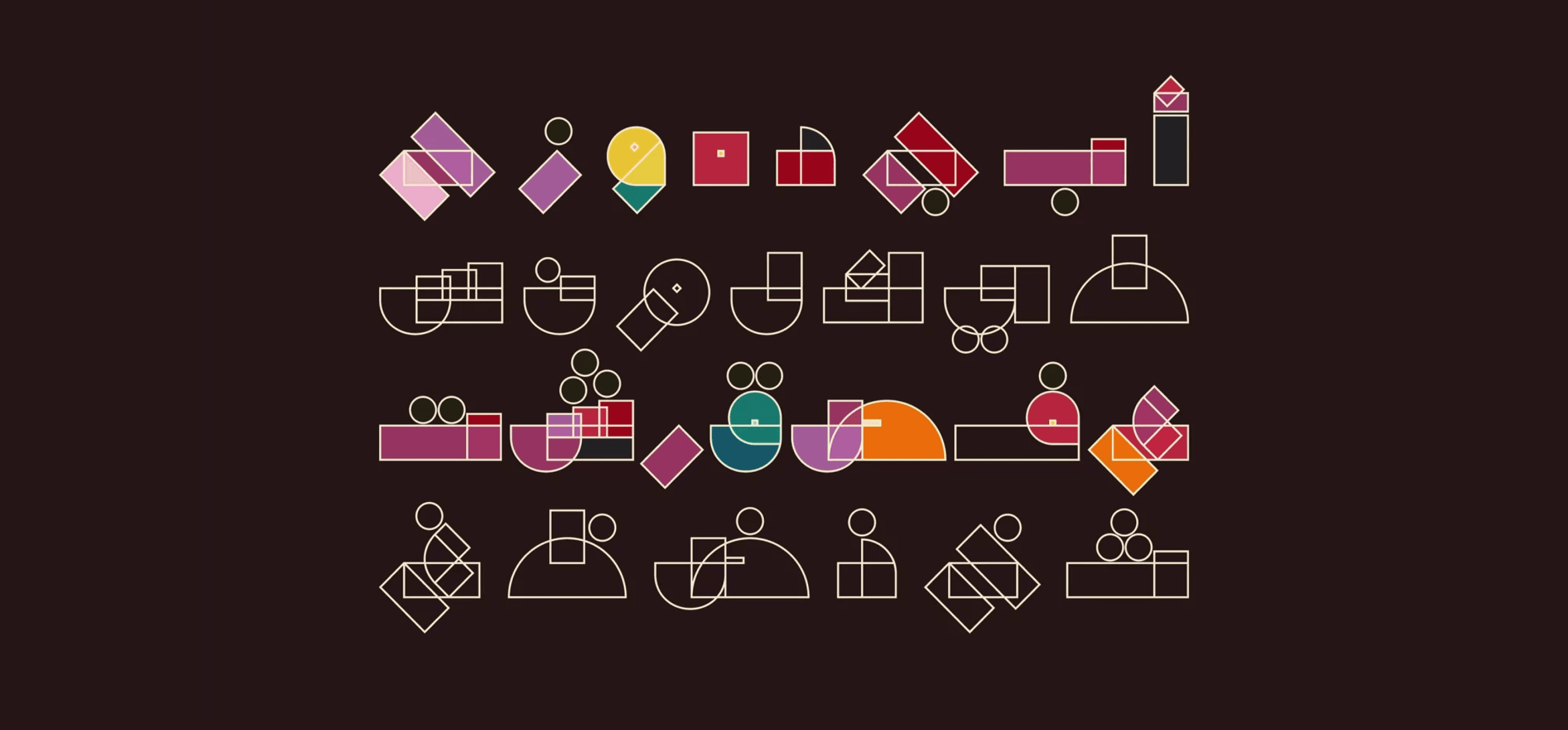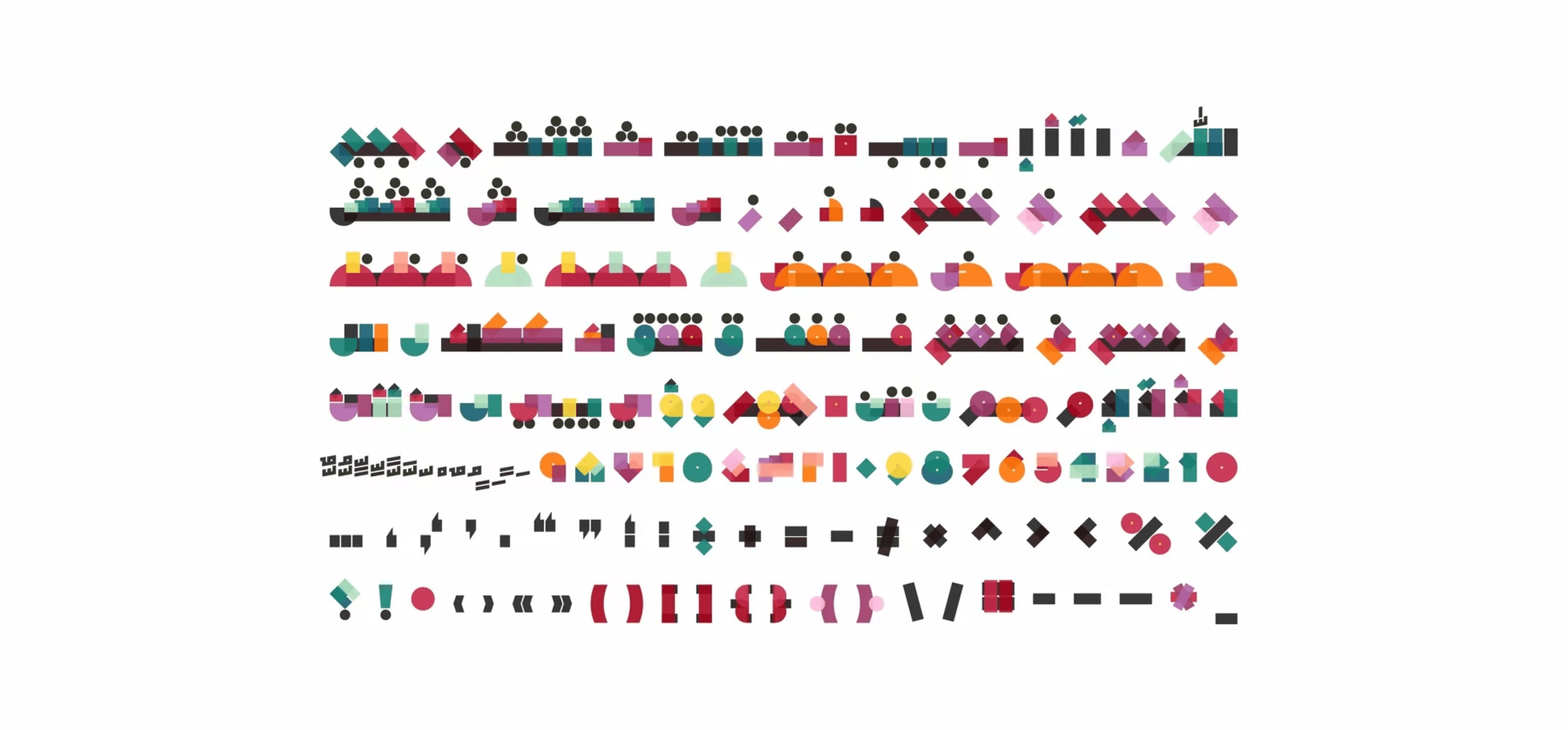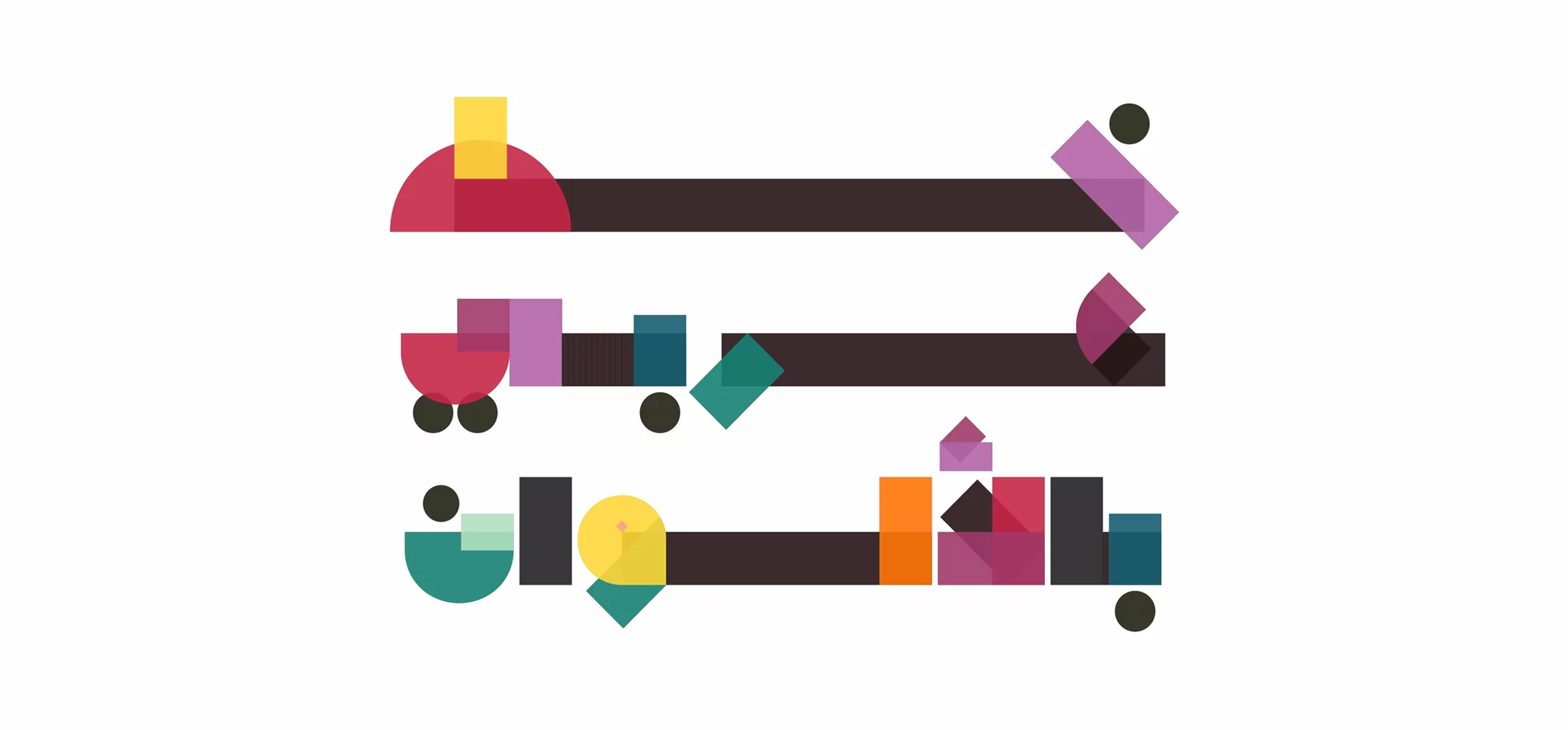
خط Momaykan (وتعني "مُمَيكن" أو "آلي" بالعربية) هو خط عرض عربي يتميز بأشكال حروف هندسية بسيطة تعكس الطابع العصري والرقمي. ينتمي إلى فئة خطوط OpenType-SVG ويتكون من ثلاث نسخ ملونة (ملوّن، ملوّن بإطار 1، ملوّن بإطار 2) بالإضافة إلى إصدار تقليدي بخط OTF عادي (Outlined).
تم تصميم Momaykan ليناسب المشاريع الحديثة مثل تصميم الويب، المطبوعات، وتطبيقات الهواتف، حيث يجمع بين الحداثة، والبساطة البصرية، وديناميكية الألوان، مما يجعله خيارًا مثاليًا لتصاميم جريئة ومتميزة.